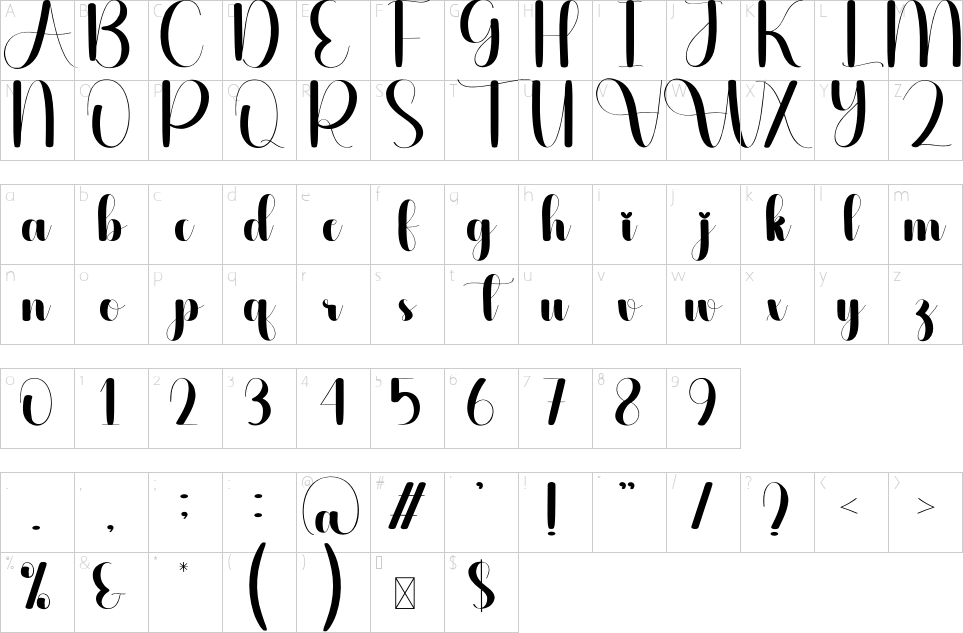
Adventure Font – Download Grátis
A Adventure Font é uma fonte cheia de aventureirismo e criatividade, perfeita para aqueles que buscam um toque diferenciado em seus projetos digitais. Desenvolvida por scratchones, esta fonte foi descarregada por 505 pessoas e é um excelente recurso para designers digitais e criativos. Seja para criar o próximo romance, uma revolucionária interface de usuário ou simplesmente para adicionar um toque único a um layout, a Adventure Font traz uma riqueza de detalhes e personalidade. Com linhas definidas e uma tipografia vibrante, esta fonte é uma ótima escolha para aqueles que buscam um desafio visual sem abrir mão de uma estética profunda e atraente. Descubra por si mesmo o que a Adventure Font pode fazer pela sua próxima criação.